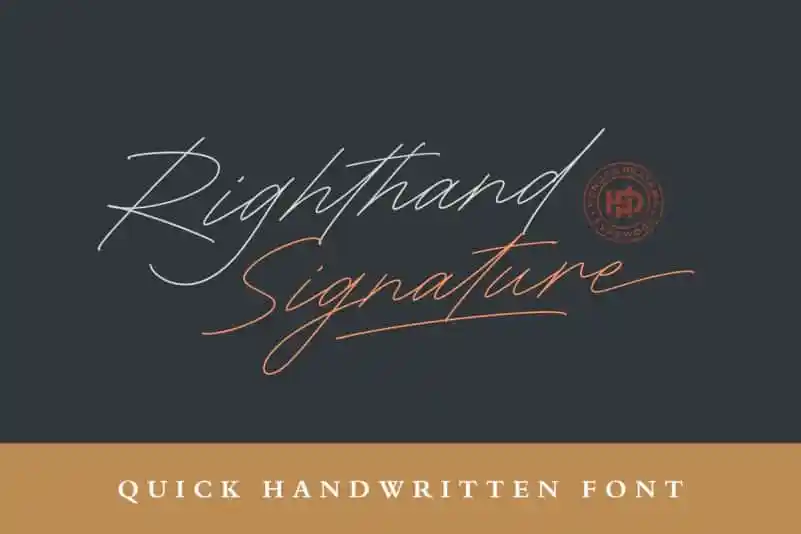
Righthand Handwritten Font – Download Grátis
A Righthand Handwritten Font é uma fonte criada por Hendra Pratama com um visual natural e vibrante. Seu design elegante e dinâmico dá vida a qualquer projeto onde ela seja usada. Esta fonte se destaca quando combinada com uma fonte sans-serif geométrica ou serif, adicionando sofisticação e personalidade ao seu trabalho. A Righthand Handwritten é perfeitamente adequada para aplicativos criativos como invitations de casamento, postais e gráficos monogramas. Seja você um designer que busca diversificar o seu portfólio com uma fonte única ou um editor de imagens que está buscando algo diferente e sofisticado, a Righthand Handwritten Font será uma escolha inteligente para complementar seus projetos digitais.